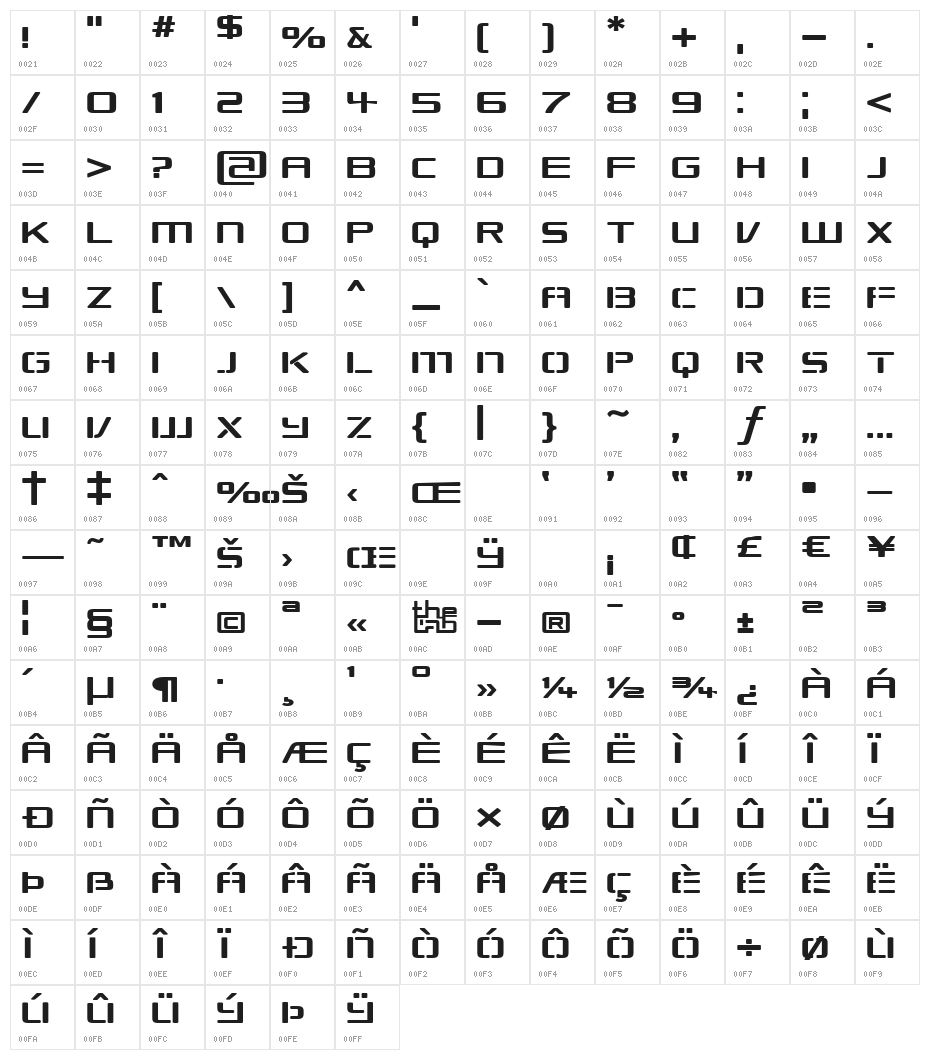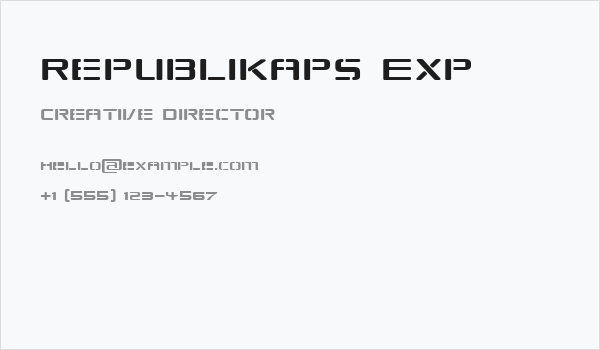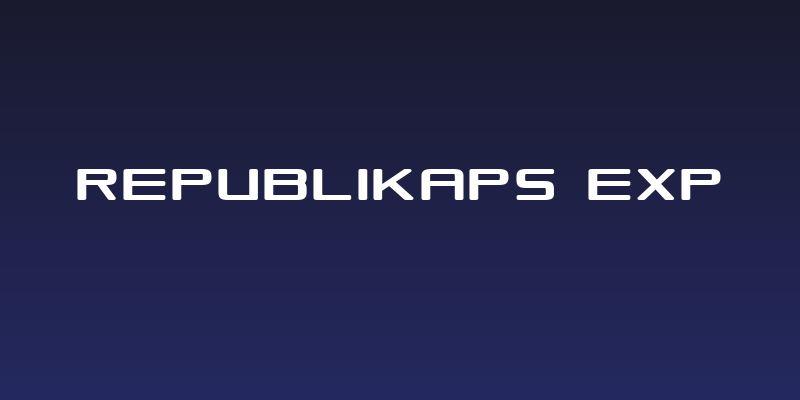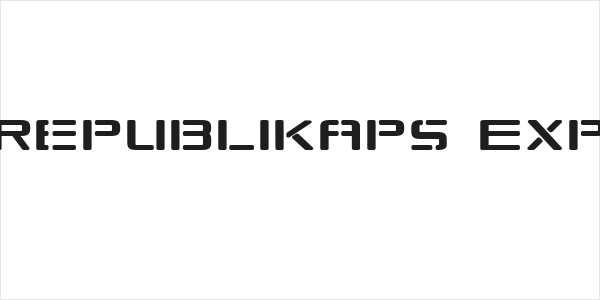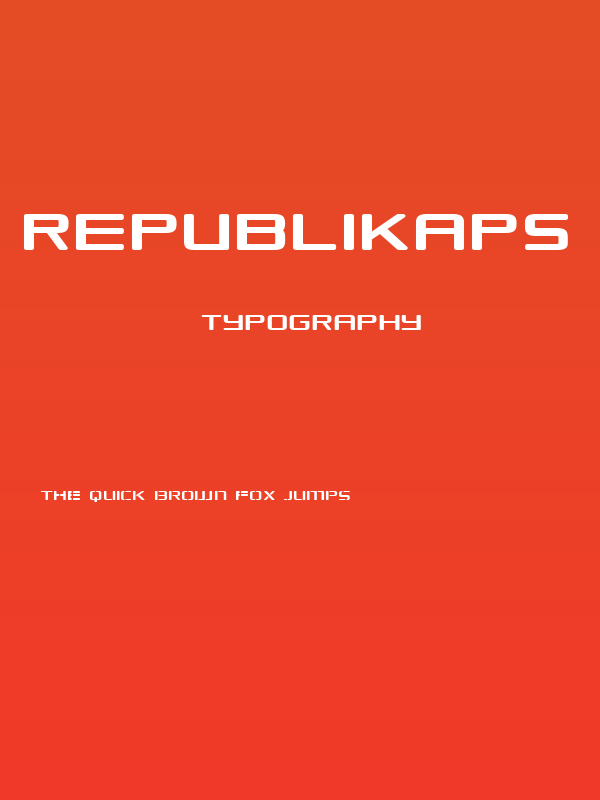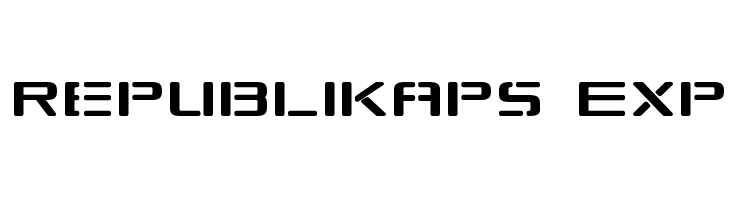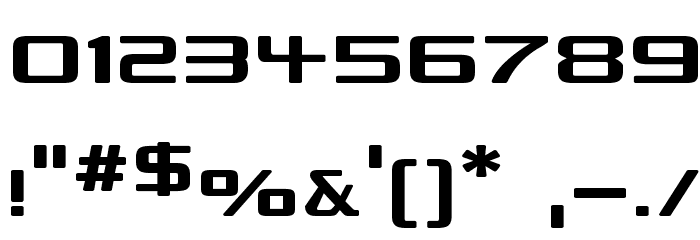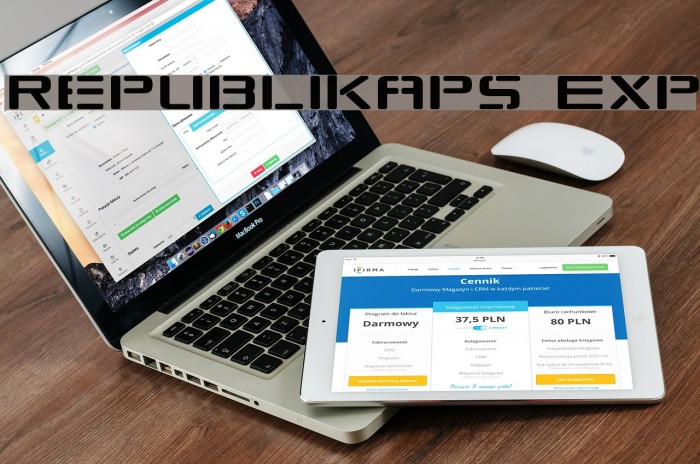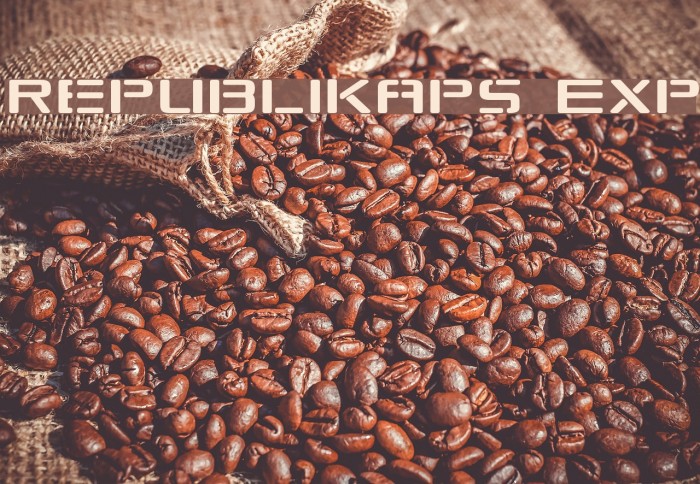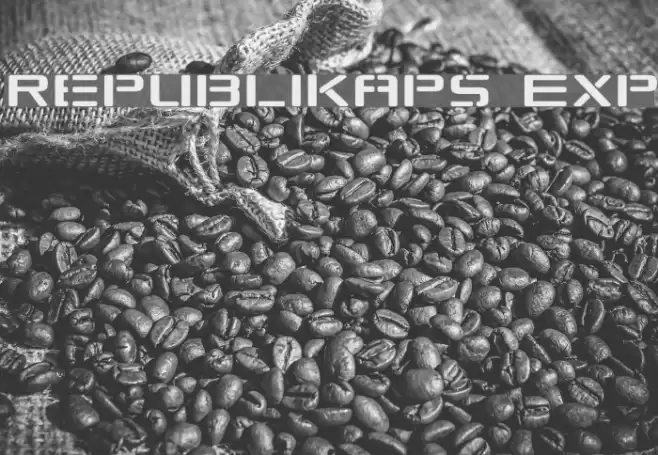
Republikaps Exp Font
Fonts by Apostrophic Lab
| Anwendungsfall | Headlines, Logos, Digital Interfaces |
| Vorgeschlagene Projekte | Ideal for technology branding, futuristic posters, digital interfaces, and modern advertising campaigns. |